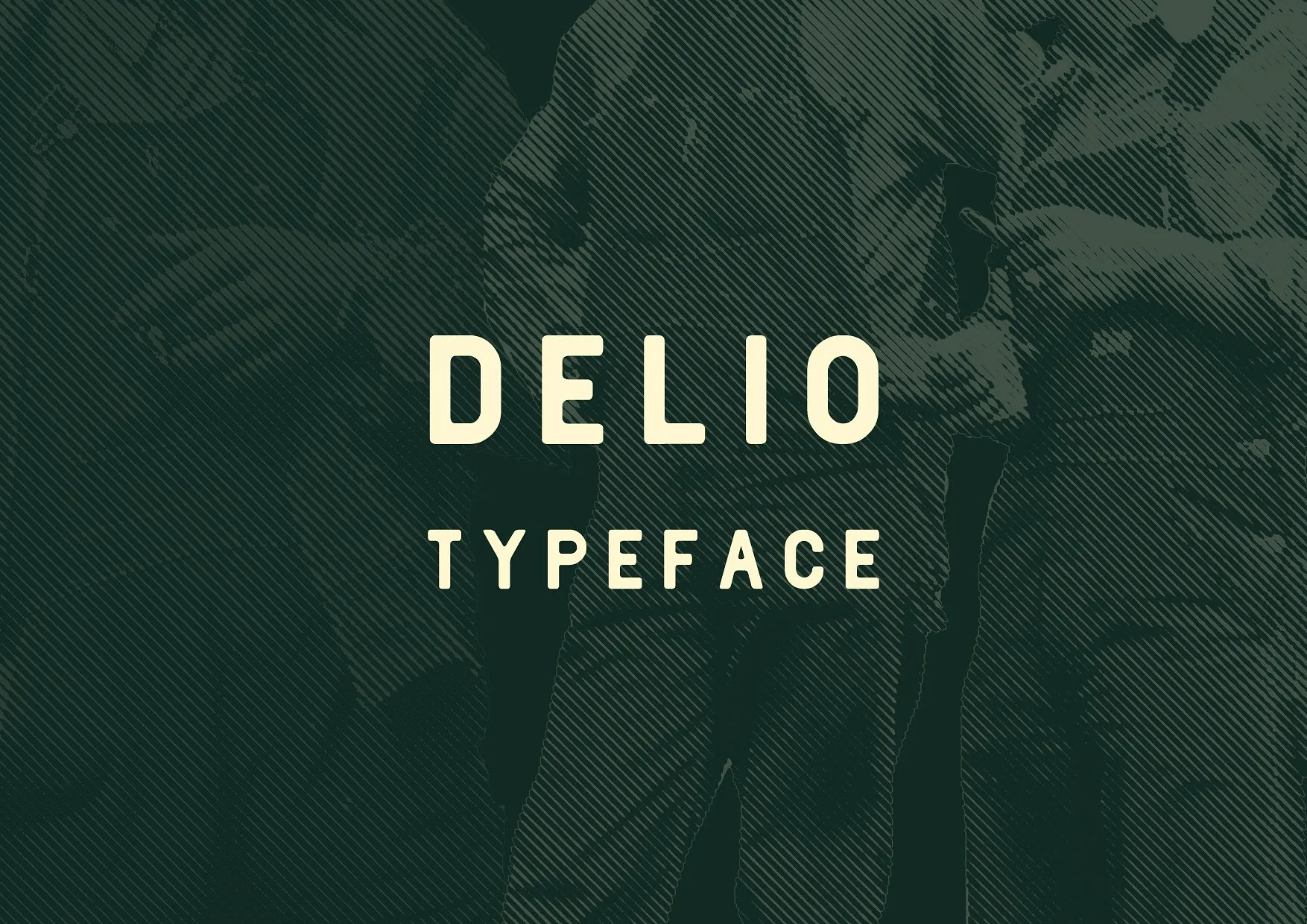
A Delio Typeface é uma fonte que combina elegância vintage com um toque moderno, perfeita para criar logomarcas ou qualquer projeto que exija um ar retrô e desenhado à mão. Inspirada no ambiente industrial, essa fonte se destaca por sua atmosfera onde os trabalhadores ou técnicos lidam com grandes máquinas. Com ângulos redondos e alto x-height, ela foi projetada para ser aplicável em rótulos dentro da sala de produção na fábrica. Esta fonte traz uma combinação única e interessante de formas robustas que evocam o passado industrial, mas com linhas retas e diretas que refletem a natureza moderna das máquinas atuais. Ela é perfeita para qualquer projeto que necessite de um olhar cuidadoso sobre detalhes, desde logomarcas até rótulos ou design em geral. A Delio Typeface não só oferece uma aparência contemporânea e moderna, mas também mantém o charme das fontes serifadas, criando um equilíbrio perfeito entre antiguidade e inovação.